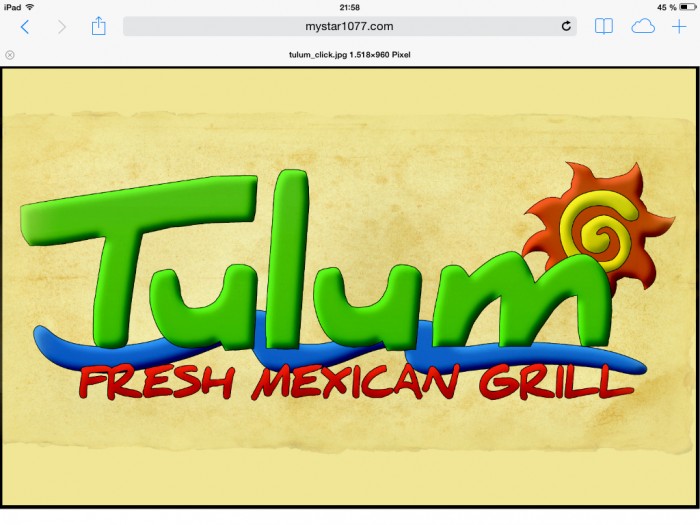
Schriftart gesucht (Tulum)
Ich suche schon seit Tagen diese Schriftarten oder halt ähnliche - leider erfolglos.
Gelöst von ThierryM
Daniel Black.
"Tulum" ist auch daraus aufgebaut: die u mit einem Abstrich versehen, alles begradigt und aufgefettet.